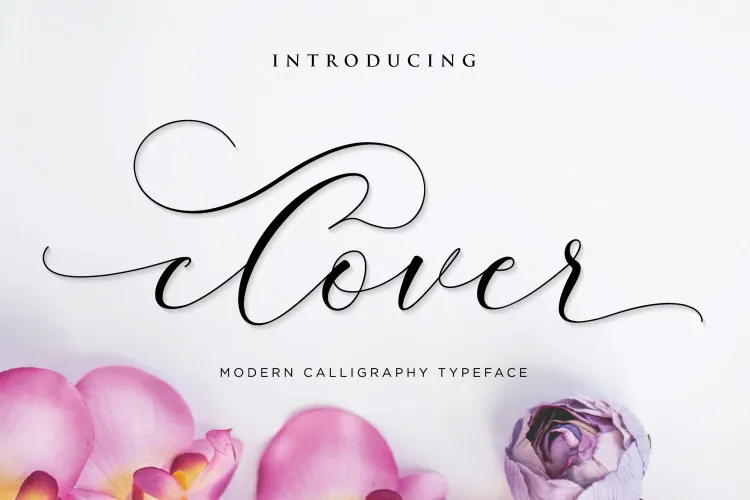
Clover Calligraphy Font – Download Grátis
A fonte ‘Clover Calligraphy Font’ é perfeita para quem busca uma gravação elegante que adicionará um toque feminino aos seus projetos digitais. Esta opção de script, desenvolvida pelo designer fantastudio, traz características únicas e harmoniosas ao estilo da gravação de prata, combinando a delicadeza com o jeito das mãos. A fonte ‘Clover’ não é apenas um recurso para personalizar seu design, mas também uma representação visual do feminino no universo digital. Suas curvaturas excepcionais e estilo clássico criam um contraponto perfeito às formas tradicionais, tornando-a ideal para uso em convites, rótulos de embalagem, menus, logotipos, moda, material de estação, impressão à mão, romances, revistas, livros e cartões de cumprimentos ou aniversários. Sua simplicidade e sofisticação fazem dela uma opção versátil para diversas áreas do design, tornando-a não apenas uma ferramenta útil, mas também um adorno visual atraente.